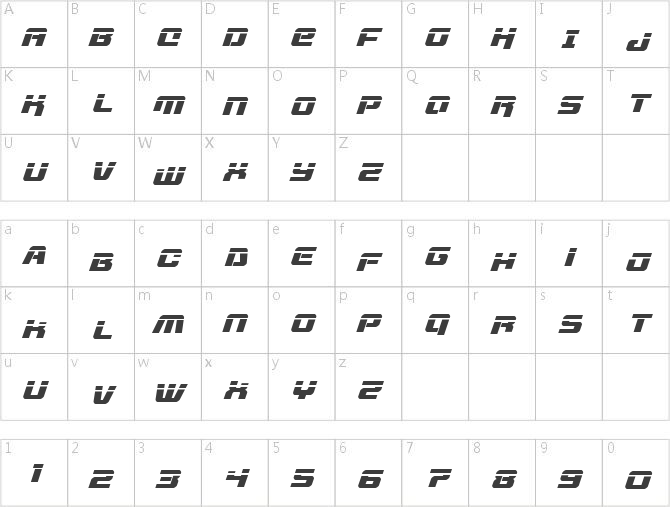
Livewired Laser Italic
Livewired Laser Italic介紹
Livewired Laser Italic字體字庫是一款讓人賞心悅目、百看不厭的英文字體,適合各類廣告和產品包裝設計應用,字體大小0.03MB,格式為ttf字體,上傳用戶是釜源貿易,作者/版權方為未知